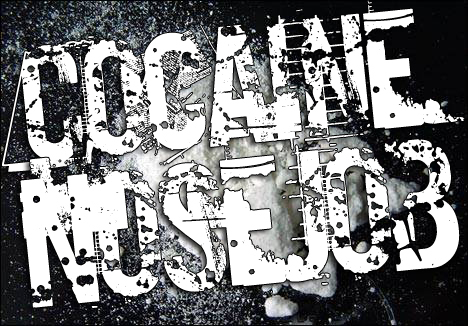
Cocaine Nosejob to darmowy krój typu display o surowym, zniszczonym charakterze, stworzony przez Pennyzine w 2008 roku, który nawiązuje do estetyki ksero-punka. Jego wysokie wielkie litery są pełne wyszczerbień, rys, plam i faktur rozdartego papieru, a nieregularne krawędzie i nagłe zmiany kształtów nadają literom niespokojny, buntowniczy wyraz.
Ta poobijana powierzchnia przywołuje skojarzenia z plakatami koncertowymi i okładkami niezależnych magazynów. Wykorzystaj ten darmowy font w oprawie płyt, markach odzieży skate, grafikach protestacyjnych czy ulotkach imprezowych, gdzie jego poszarpane warstwy idealnie współgrają z fotografią i surowym kolażem, nie tracąc przy tym swojego zadziornego charakteru.